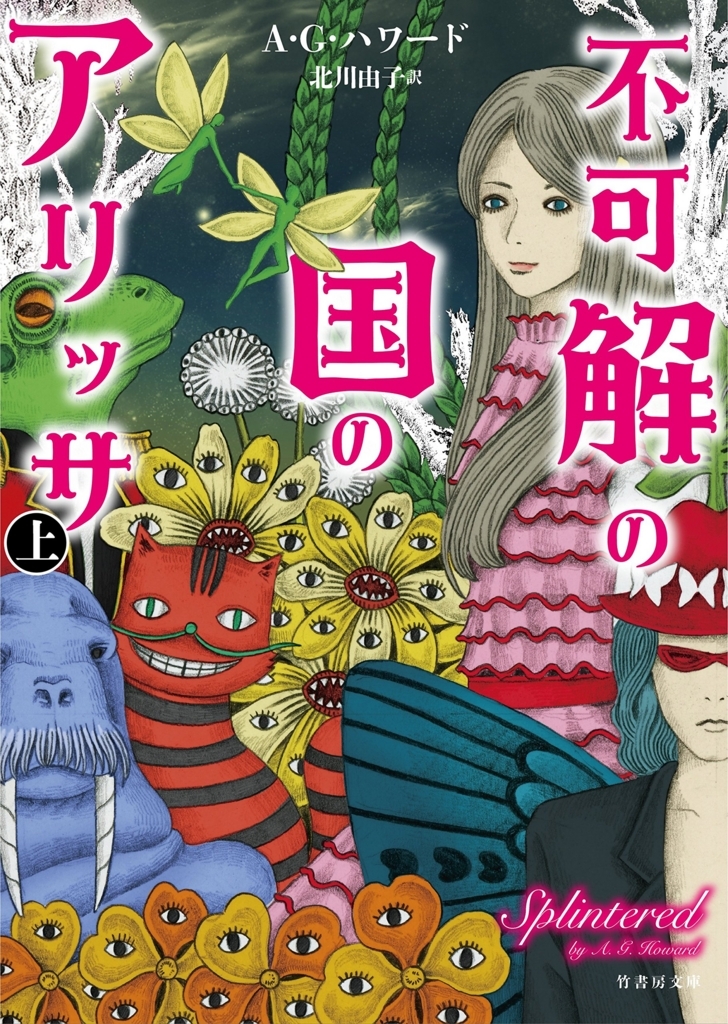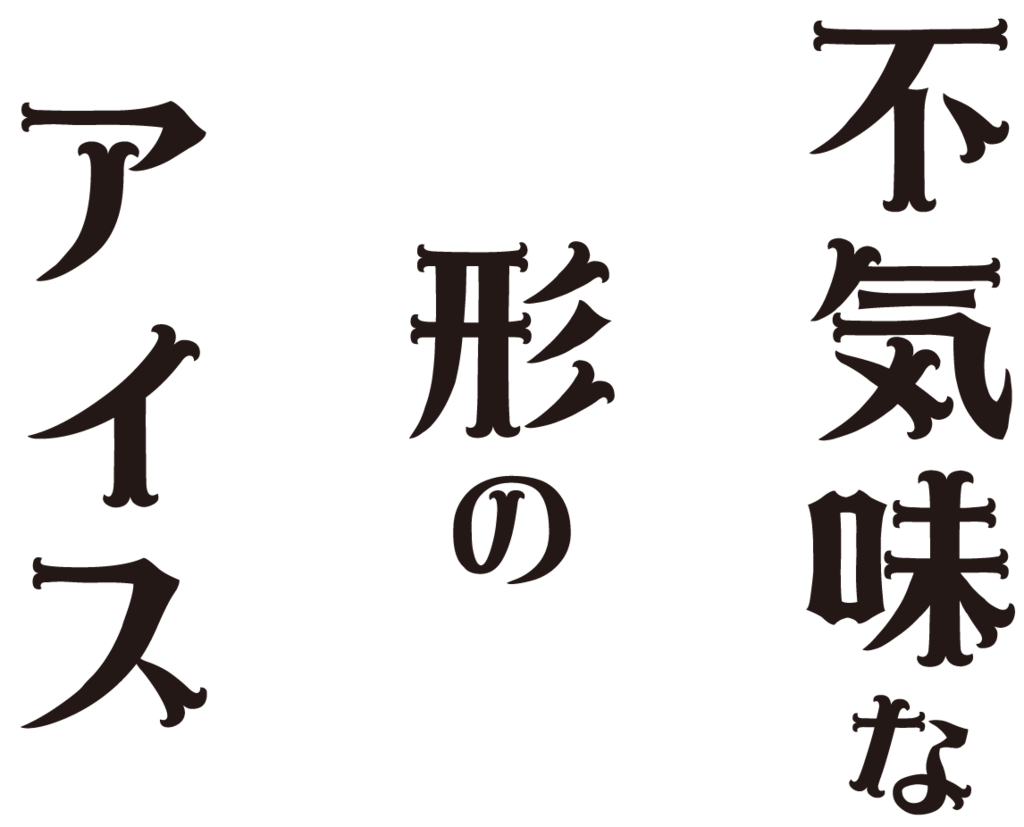
不可解の国のアリッサ
A.G.ハワード氏著書、日月沙絵氏イラスト、北川由子氏翻訳による小説「不可解の国のアリッサ」は上下巻で竹書房から2016年6月30日に発売。
不可解の国のアリッサのタイトルのフォントにロマン輝が採用
「不可解の国のアリッサ」のタイトルにダイナフォントのロマン輝が採用されている。
ロマン輝
大正時代の伝統的な明朝体に、昭和初期に発行された書籍のタイトル部分の特徴を組み合わせてデザインされた書体。縦画、横画、左はらい、右はらいなどのエレメント中に欧風装飾が加えてられており、クラシカルなスタイルの中に現代的な華麗さも表現された。